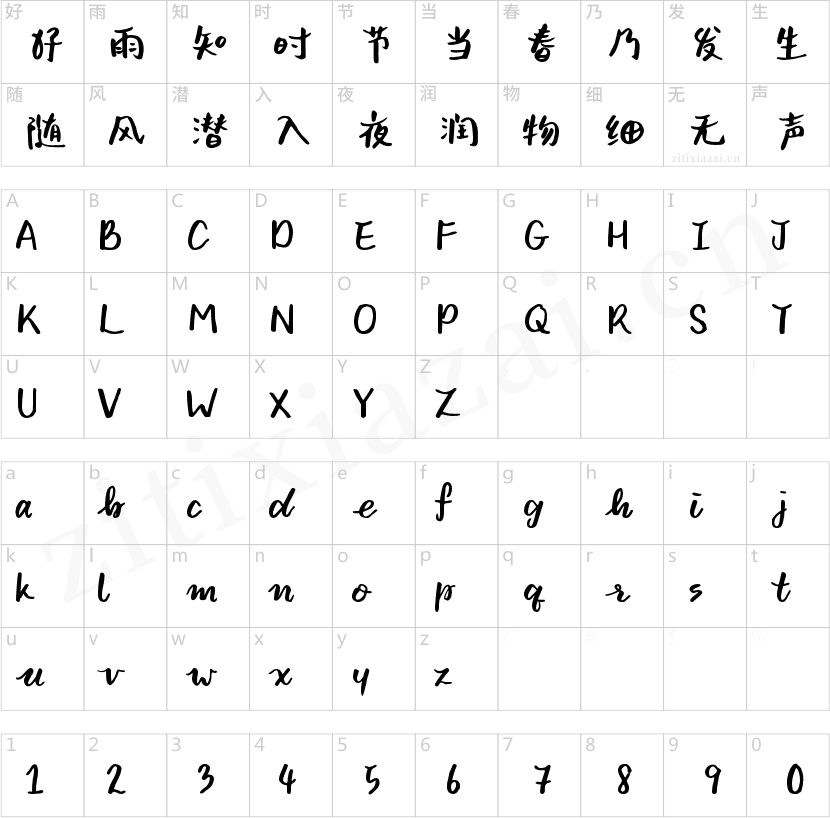
Aabook思议
Aabook思议字体
Aabook思议是一款非常具有艺术性的字体,它的设计灵感来源于对古典艺术的研究,同时又融入了现代字体设计的元素。字形优美,笔画粗细变化自然,给人以大气、典雅的感觉。Aabook思议是一款既传统又现代的字体,它的设计充满艺术感,美观大方,实用性也非常强。无论是对于设计师还是对于普通读者来说,都是一种非常不错的字体选择。Aabook思议适合用于具有艺术感的场合,比如海报、宣传单张、书籍封面等。由于其字形流畅且具有动态感,也适合用于大量的文本排版,如报纸、杂志等。